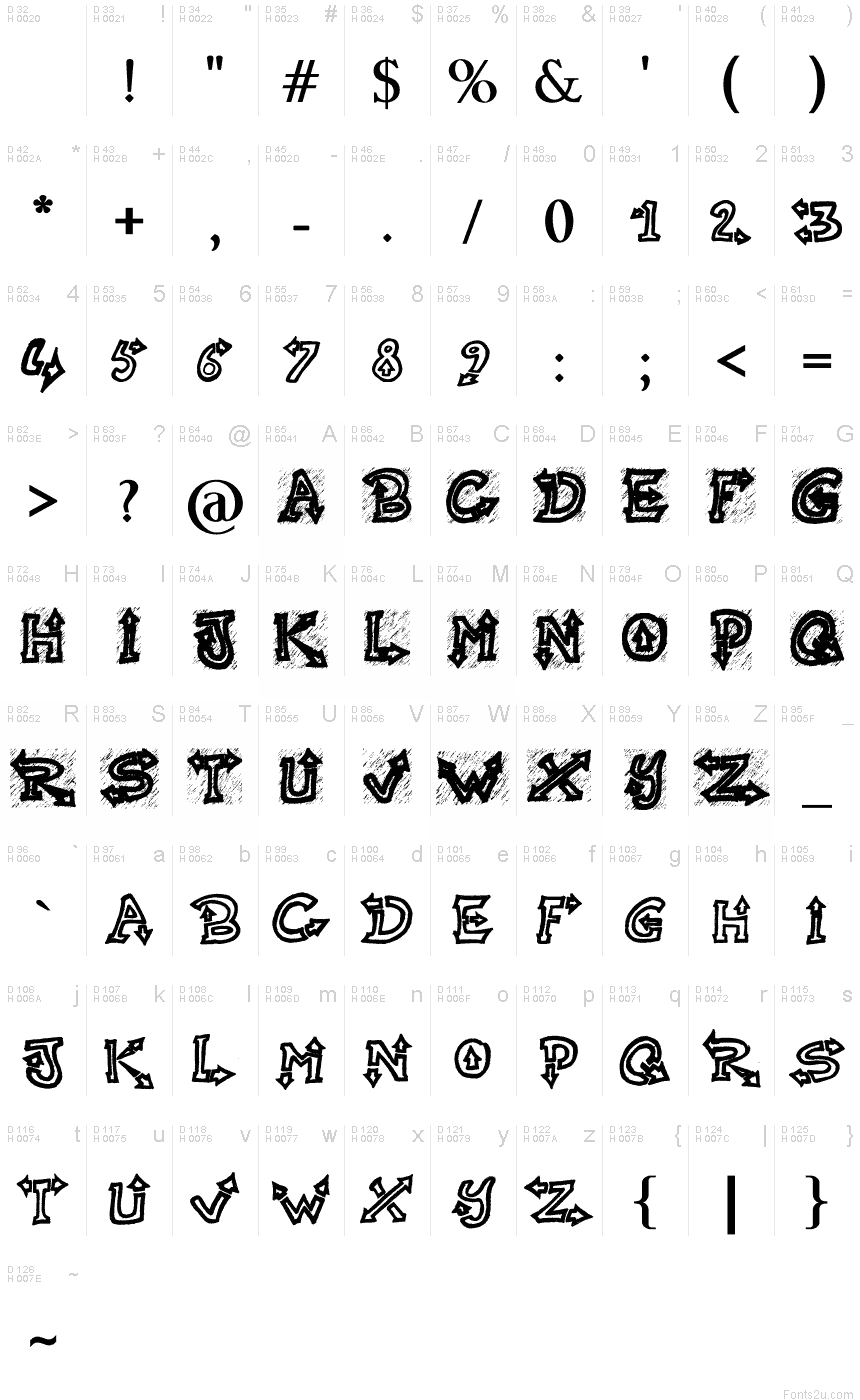
Raslani Undaground Bold
Raslani Undaground Bold autorstwa le Raslani to darmowy krój pisma w stylu graffiti, z surową energią ulicznego markera. Litery są grube i nierówne, nakreślone niczym szybkie, odręczne tagi, z grotami strzałek wkomponowanymi w kreski i zadziorną, „nabazgraną na ścianie” energią, która sprawia, że cały zestaw wydaje się pełen niepokoju.
Pasuje do plakatów, okładek mixtape’ów, grafiki skate, zinów i ulotek, gdzie lettering potrzebuje raczej surowego, improwizowanego sznytu niż wygładzonej elegancji. Jako darmowy font świetnie sprawdzi się też w tytułach, krótkich nagłówkach i monogramach, bo dzięki wbudowanym strzałkom nawet kilka liter zyskuje charakter pełnowymiarowego graffiti.